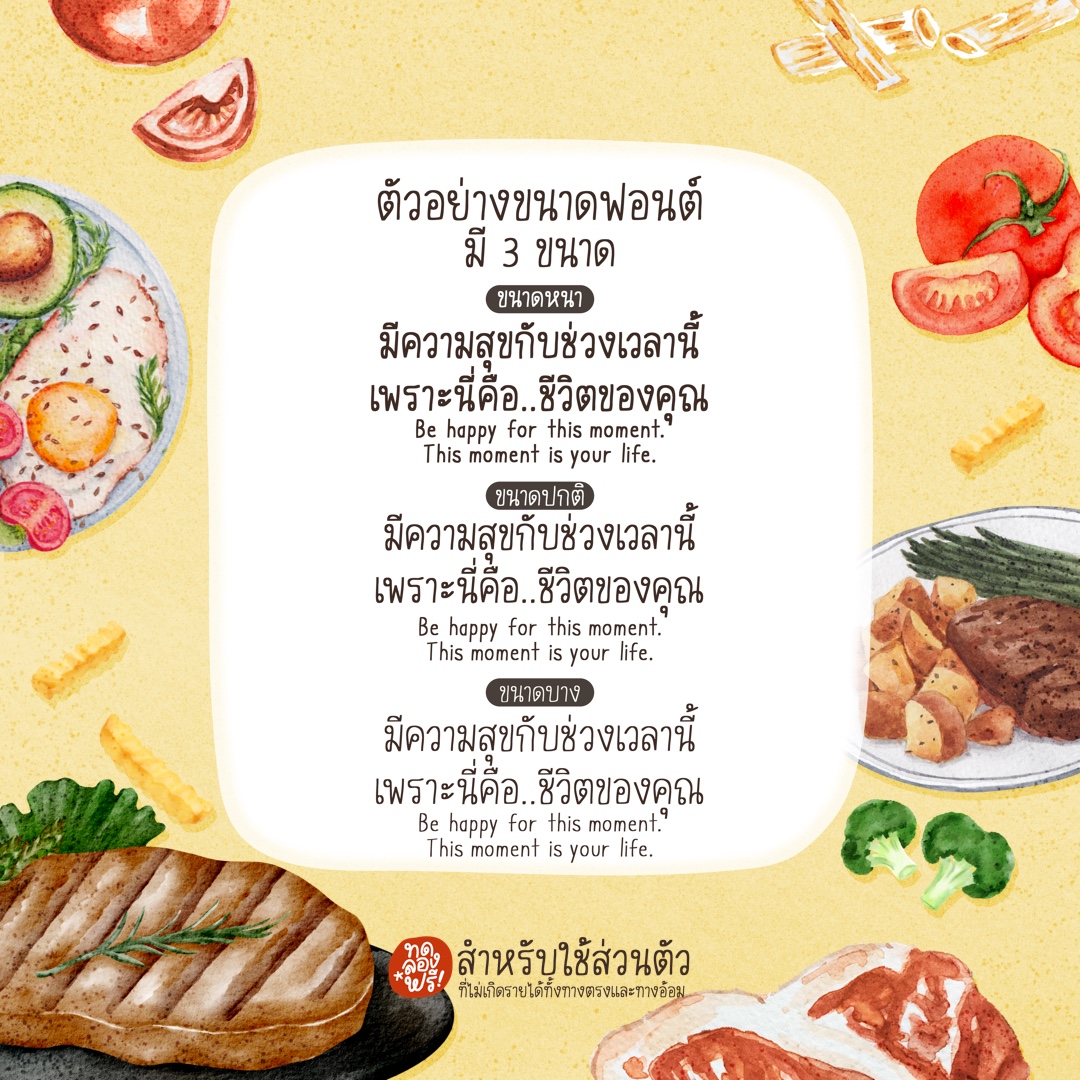
พอร์คชอร์ป (PG Porkshop)
ฟอนต์ลายมือสไตล์น่ารักปุ๊กปิ๊ก อ่านง่าย รองรับ Microsoft, Photoshop, Illustrator, CapCut, ibisPaint, Procreate, Good Note และแอปฯ ต่างๆ ที่มีให้ติดตั้งฟอนต์